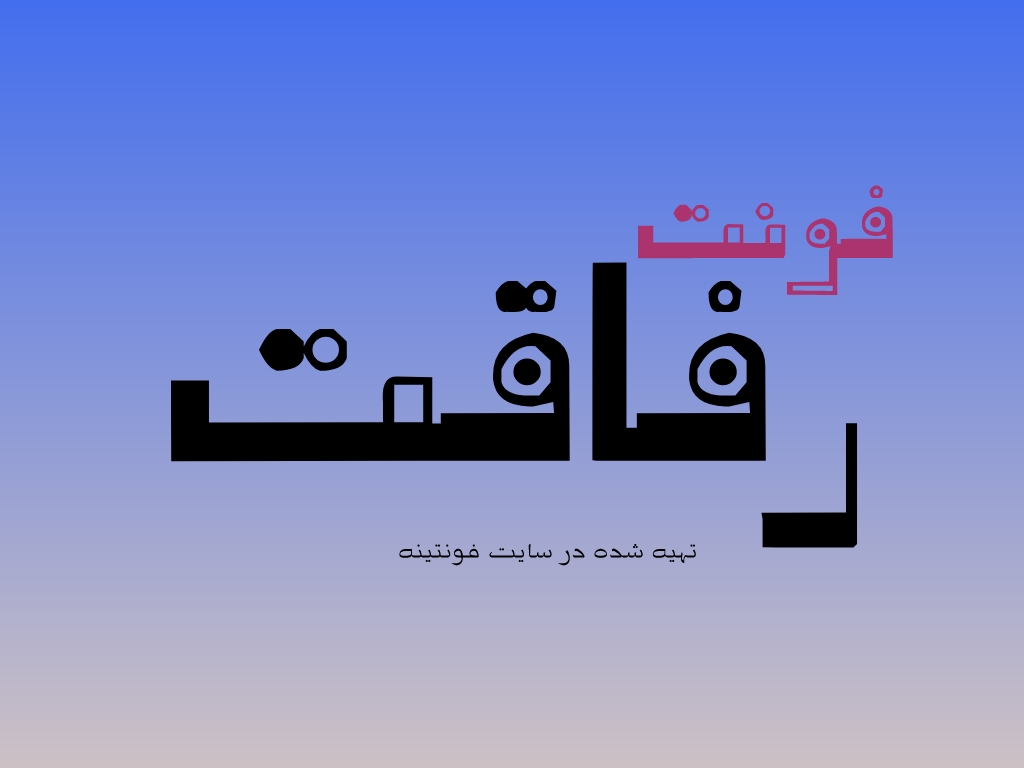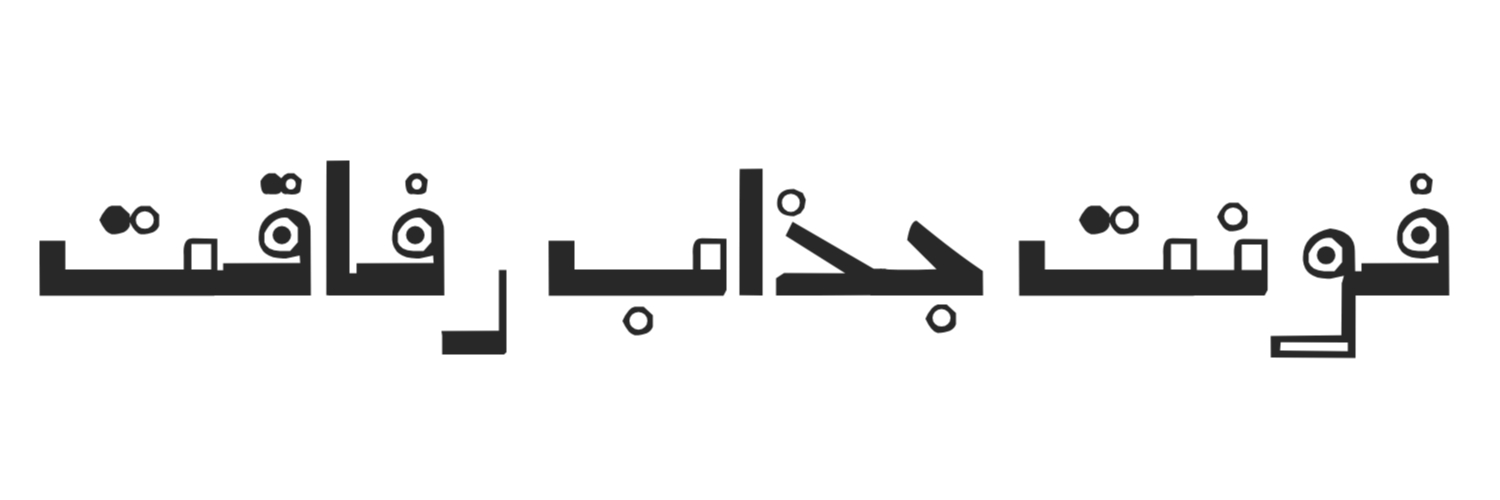
دانلود فونت رفاقت در خدمت شما بزرگورارن هستیم با ارائه فونت زیبا و فارسی رفاقت این فونت برای طراحی های لوگو و بنر و…. مورد استفاده قرار میگیرد.
ویژگی های فونت :
• مدرن و کاربردی
• زیبا و خاص
• مناسب طراحی لوگو و بنر
تصاویری زیبا از طراحی های خاص با فونت رفاقت که برای نمایش و نمونه پیش فرضی از نمایش این فونت کاربردی طراحی شده است
فونت جذاب رفاقت